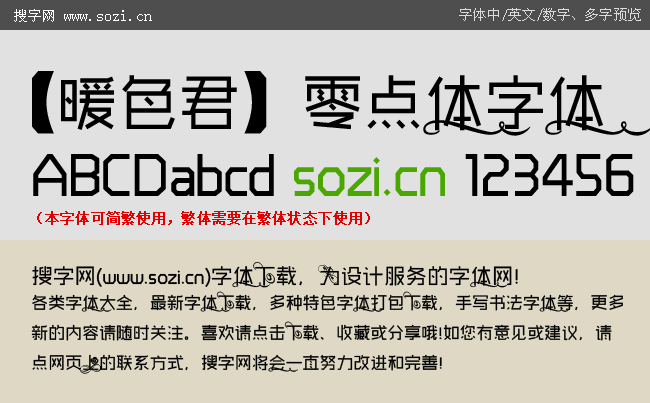
零點(diǎn)體字體
搜字網(wǎng)給大家提供一款零點(diǎn)體字體手機(jī)中文字體下載。這款手機(jī)字體是將黑體字體進(jìn)行重新設(shè)計(jì),更加具有藝術(shù)感,字體間又裝飾上了漂亮的花紋。是一款非常藝術(shù)的字體,特別適合喜歡手機(jī)字體個(gè)性一些的朋友在手機(jī)上安裝使用。